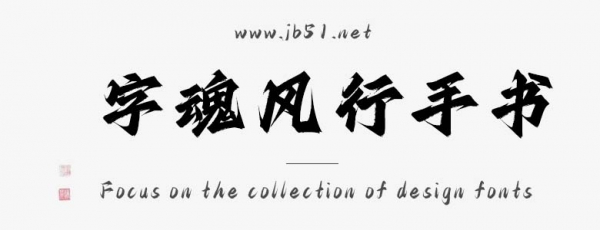
字魂風(fēng)行手書是由字魂字庫(kù)推出的硬筆手寫,創(chuàng)意字體,該字體包含9503個(gè)中文、字母、 符號(hào)和數(shù)字,具有時(shí)尚的風(fēng)格,可以滿足您設(shè)計(jì)上的各種需求,適合應(yīng)用于藝術(shù)設(shè)計(jì)、平面宣傳設(shè)計(jì)、網(wǎng)頁(yè)設(shè)計(jì),書法字帖等領(lǐng)域。
字魂風(fēng)行手書字體是一款商用的硬筆手寫,創(chuàng)意字體,該字體包含9503個(gè)中文、字母、 符號(hào)和數(shù)字,具有時(shí)尚的風(fēng)格,可以滿足您設(shè)計(jì)上的各種需求,該字體主要用于標(biāo)題字等場(chǎng)景, 您不但可以在字魂網(wǎng)下載字魂風(fēng)行手書字體,同時(shí)還有眾多毛筆書法字體、創(chuàng)意字體等可供選擇!